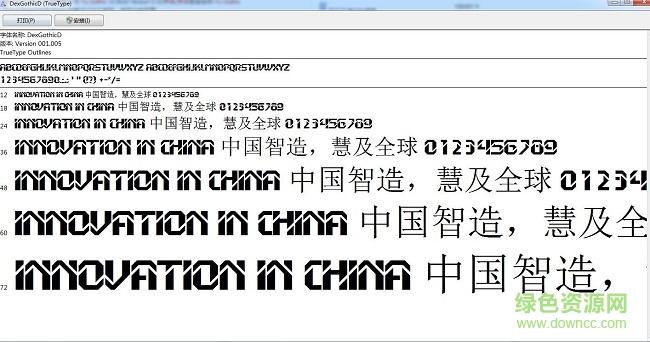
dexgothicd字體是一款特征鮮明的英文字體,完全大寫(xiě)字母顯示,字體中間自帶劃痕,一筆一畫(huà)構(gòu)造嚴(yán)謹(jǐn),帶有機(jī)械感,可以應(yīng)用于網(wǎng)頁(yè)設(shè)計(jì)中,效果絕對(duì)醒目,需要的朋友快來(lái)下載吧!